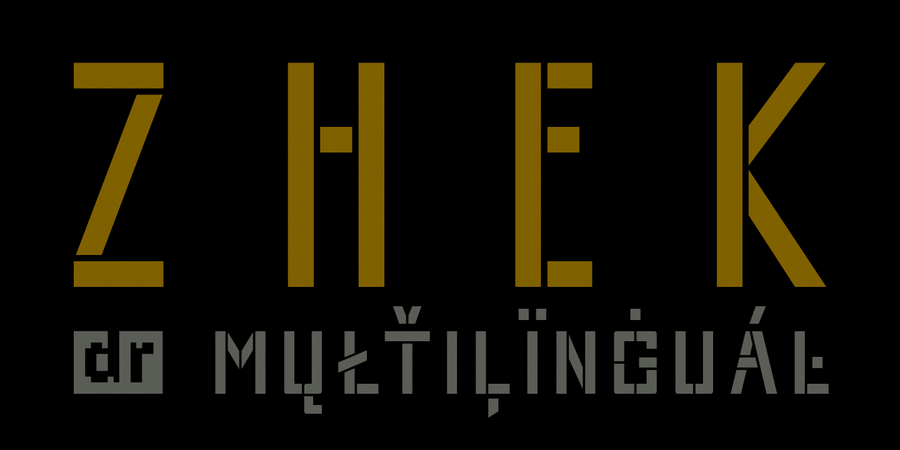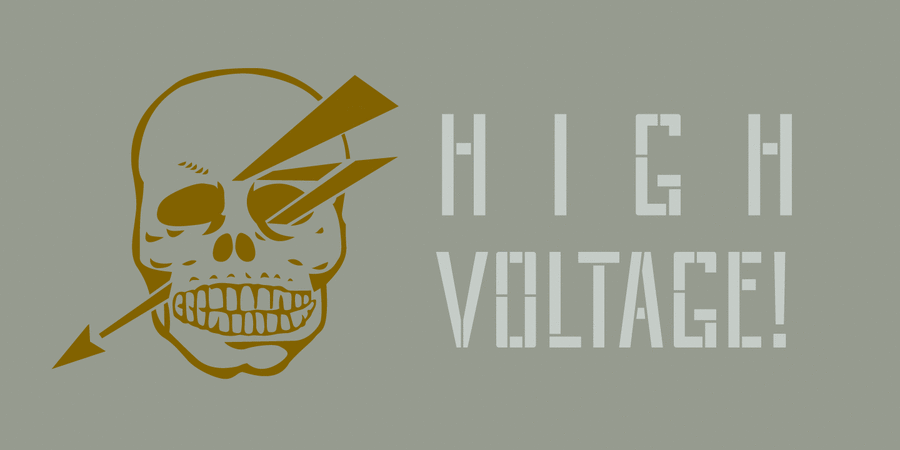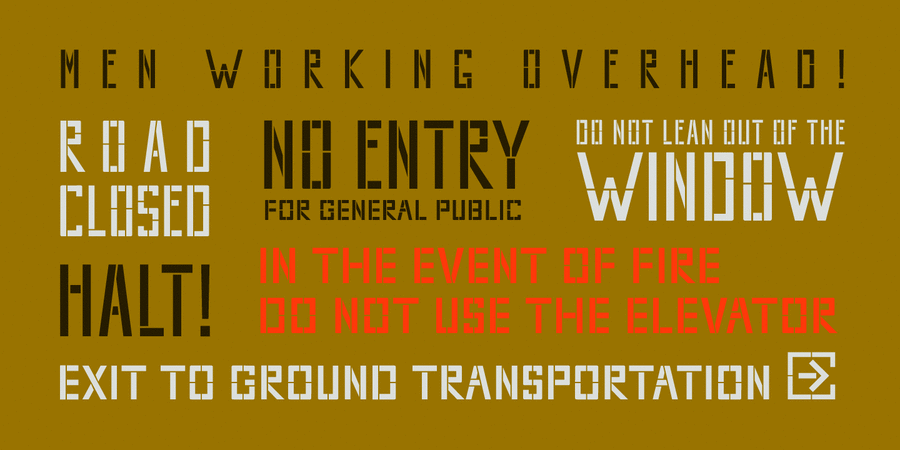
DR Zhek (1 шрифт)
ЖЕК – це брутальний вузький трафаретний паличний шрифт. Має грубий шарм робітничого класу. Дуже добре підходить для ігор, фільмів або товарів у мілітаристській та індустріальній естетиці. Шрифт розробив Дмитро Растворцев у 2017 році.
Асоціації з сімейством шрифтів DR ZhekОсобистість і характер гарнітури:
суворий, ламаний, характерний, саморобний, незграбний, радянський, портовий, яскравий, ігровий, знайомий, блатний, небезпечний, серйозний, переконливий, твердий, статичний, залізний, надійний, мужній, впевнений, сталевий, ностальгічний, тоталітарний, стабільний, гучний, рівний, сильний, кондовий, стійкий, політичний, комуністичний, революційний, сміливий, Простий, пролетарський, стиснений, економний, щільний, прямокутний, індустріальний, техногенний, військовий, армійський, солдатський, урбаністичний, грубий, робочий, мотивуючий, крутий, залізничний, амбітний, холодний, побутовий, вуличний, міський, жорсткий, чіткий, різкий, брутальний, зухвалий, екстремальний, хуліганський, вернакулярний, вінтажний, радикальний, рубаний, запальний
пошта, посилка, піротехніка, гра, боєприпас, пожежний, оборона, МНС, трамвай, нафта, кран, шутер, охорона, захист, цегла, вантажівка, війна, армія, зброя, машинобудування, прапор, мітинг, політика, шахта, завод, металургія, верстат, інструмент, будівництво, будматеріали, тара, склад, порт, ящик, патрони, конструктор, креслення, інженер, техніка, промисловість, електростанція, енергетика, ремонт, депо, шахтар, шолом, уніформа, вагон, танк, страйкбол, блокбастер, бойовик, екшен, взуття, Місто, залізниця, робочий, страйк, Протест, авто, паровоз, реп, концерт, Локдаун, цигарки Гарнітура має ознаки стилів: